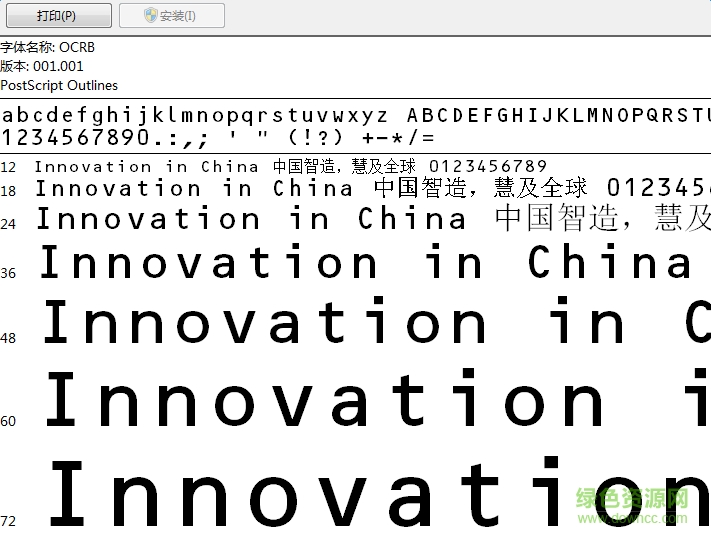
agamikocrb英文字體
agamikocrb字體是一款英文字體庫(kù)中的個(gè)性字體,該字體能夠適用于產(chǎn)品包裝、電視臺(tái)廣告、電影、電視劇片頭以及內(nèi)容用字等領(lǐng)域,喜歡的網(wǎng)友可免費(fèi)下載收藏。
agamikocrb字體是英文字體庫(kù)中一款極具個(gè)性的字體,該字體的線條粗細(xì)得當(dāng),效果處理非常棒,給用戶耳目一新的感覺(jué)。有需要就趕快來(lái)綠色資源網(wǎng)下載體驗(yàn)吧!